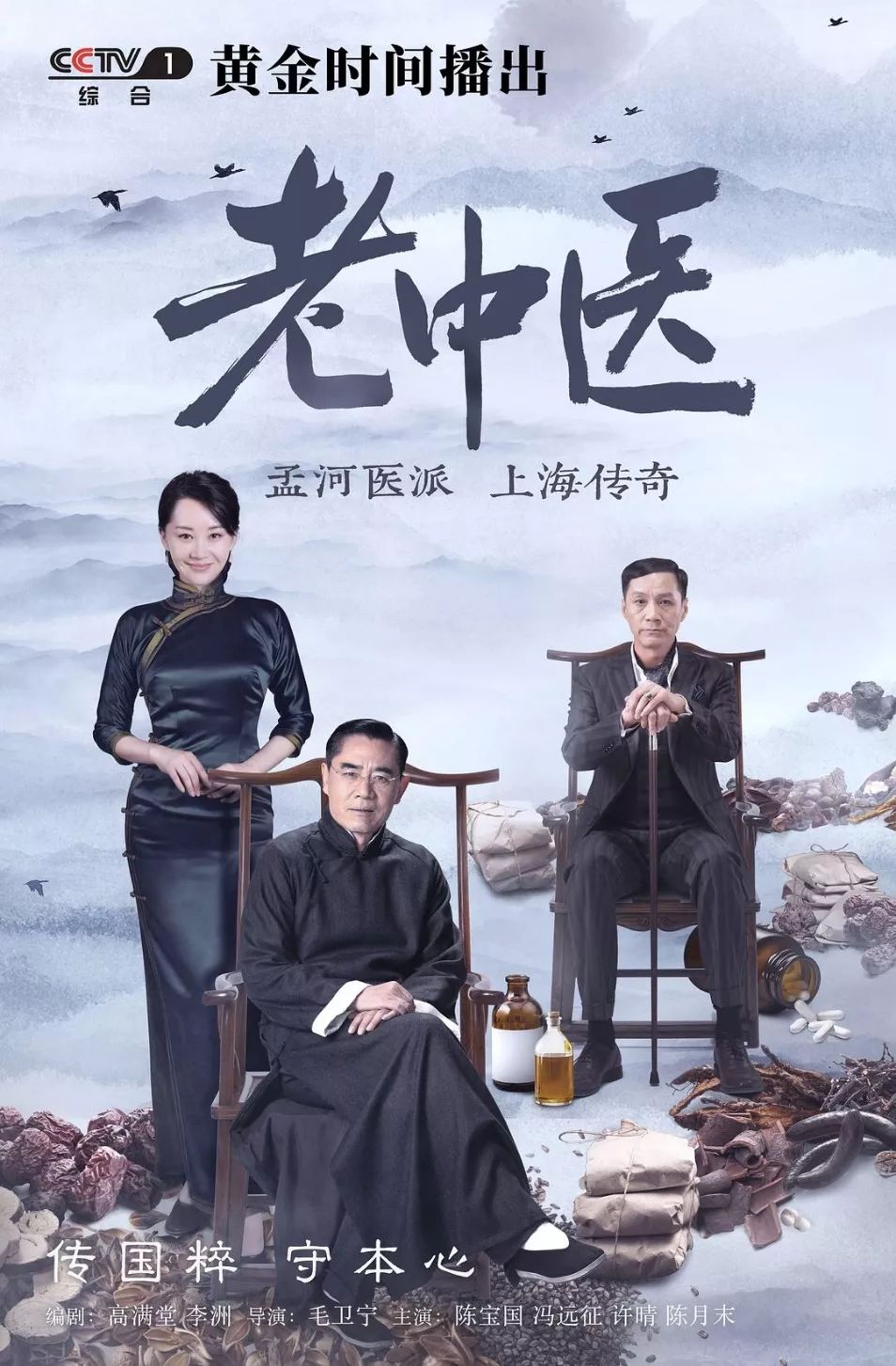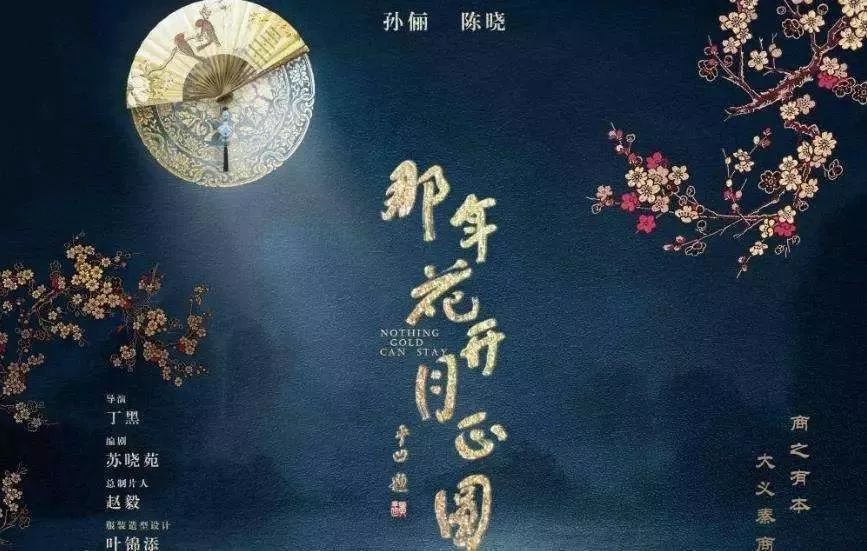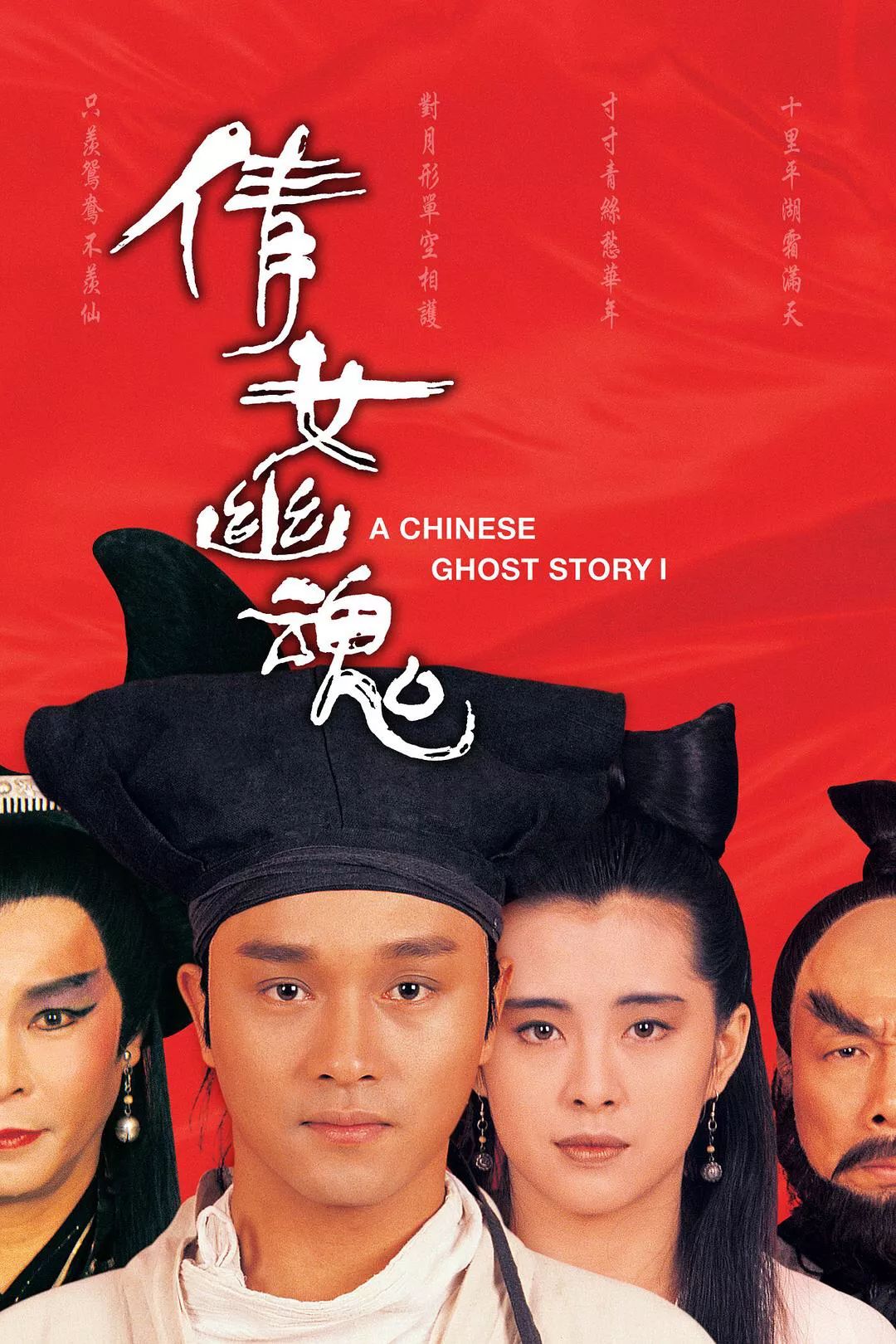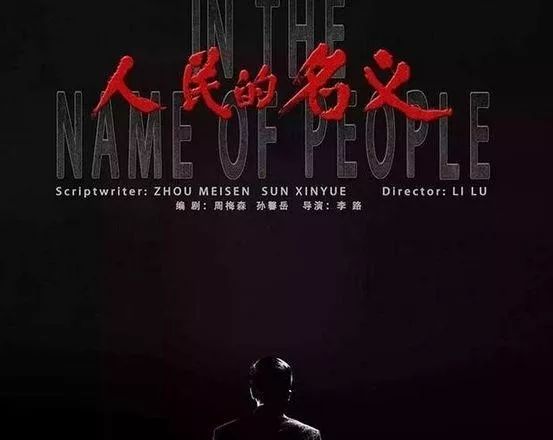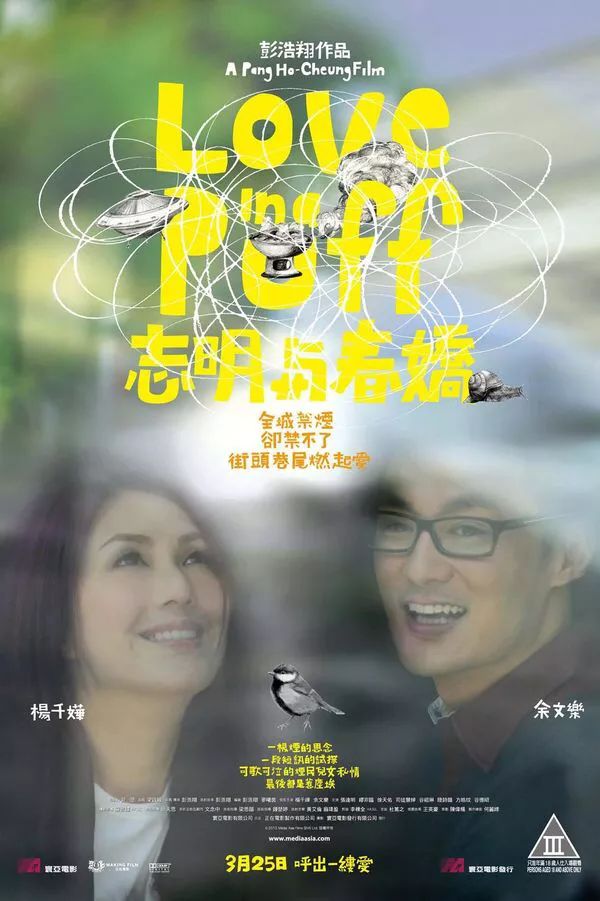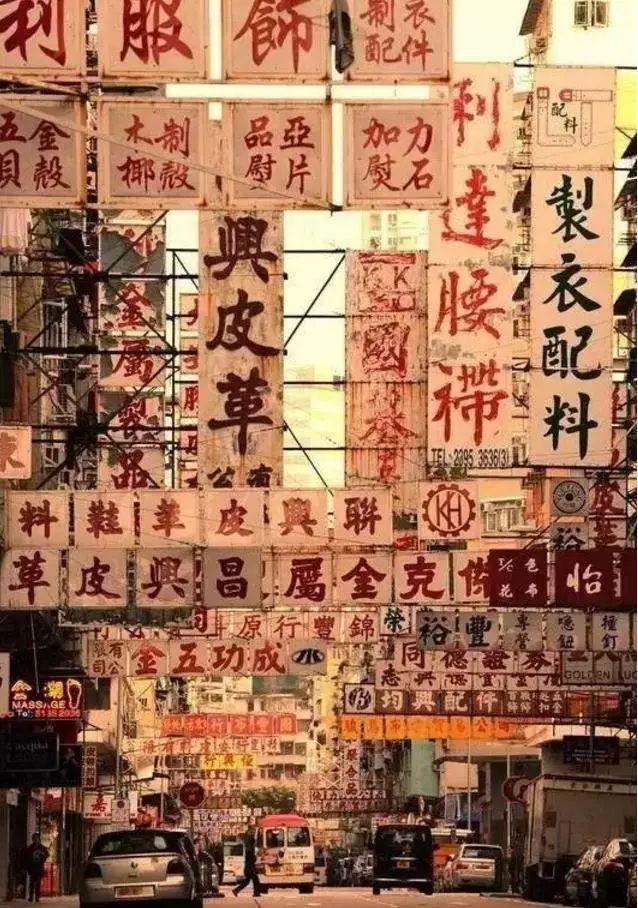
字写得好,真的可以被人记一辈子!
朋友们,最近的“国剧典范”
——《老中医》都看了吗?
网友们评价这是一部
从演员阵容到制作都非常良心的电视剧。
虽然剧情是介绍中医的,
许多人却把它当成了书法软广。
比如老中医在传授医道时提到,
学医排在第一位的是:写一手好字,
以及片头上气场十足的“老中医”三个字。
对书法史稍有了解的朋友就能看出,
这字是黄庭坚的长枪大戟的开张体势,
这种气派跟《老中医》剧情里,
誓死保卫中华瑰宝的精神如出一辙。
但这字具体是哪位书法家写的,
目前还没有人扒出来。
不过,
今天我们为大家扒了其他热播剧片头。
讲述清末陕西女首富周莹传奇一生的电视剧
——《那年花开月正圆》,
大家肯定还有印象。
片头是著名作家贾平凹题写的。
《那年花开月正圆》剧照
有人评价这七个字:
“用笔不讲究,但格调很高,
还能在字里行间看出禅意,
不失为一种独特的风格。”
贾老师的书法有没有禅意我不敢肯定,
我可以肯定的是,在众多片头里这很特别,
另一部看得人们热血澎湃的
“中国顶级政治剧”——《人民的名义》
片头背后也大有乾坤。
“人民的名义”五个字用的是颜体楷书,
楷书书体中正朴厚,一笔一画,郑重其事,
与反腐题材剧情相吻合,
试想,如果变成行书或者草书,
都会显得不够庄重,
也达不到正气凛然的效果。
颜真卿是一名出色的政治家,
安史之乱时,他的兄弟和侄子挺身而出,
却惨遭杀害,
颜真卿在极度悲愤的情况下
写了千古名篇《祭侄文稿》。
颜真卿 《祭侄文稿》
他的耿直与忠诚
形成了雄浑、宽厚、中正的颜体书风。
自此,颜体也成为正义的化身。
另一个收视爆红的抗日剧《亮剑》,
生动刻画了中国军人的
优良传统和坚忍不拔的信念。
《亮剑》剧照
这部剧的题字也是气势磅礴,凝重雄浑,
隐隐透出一股浩然正气。
导演在众多作品中,
一眼挑中了这幅苍劲挺拔的字。
“亮剑”的主人是军人出身的崔根峰将军,
他写出了军人的气质与情怀,
写出了他舒朗豁达的人生观,
也写出了导演心中的“亮剑”,
以及剧本要求的植根传统
而又冲出重围的创新精神。
崔根峰 《亮剑》
崔将军在繁忙的军事工作之余
坚持研习王羲之《兰亭序》、
颜真卿《千字文》、岳飞《出师表》等作品,
从临帖开始,渐入佳境,自成风格。
世人评价他的书法
“以军人的阳刚为主调,
给人以大江东去、一泻千里的汪洋之感,
亦不乏杨柳岸晓风残月的艺术温情与浪漫”。
和前面被人熟知的书法名家不一样,
接下来要介绍的这位片头题字者,
他的作品就有多出名,
大家就对他有多陌生。
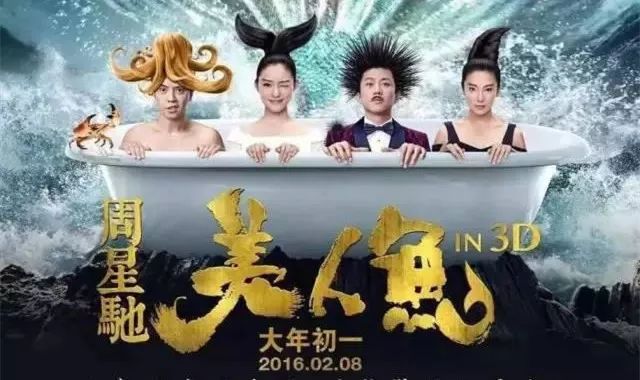
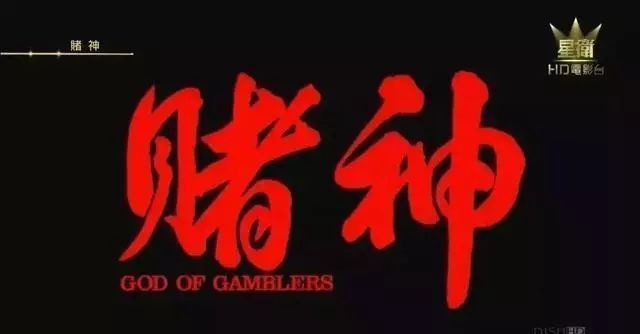
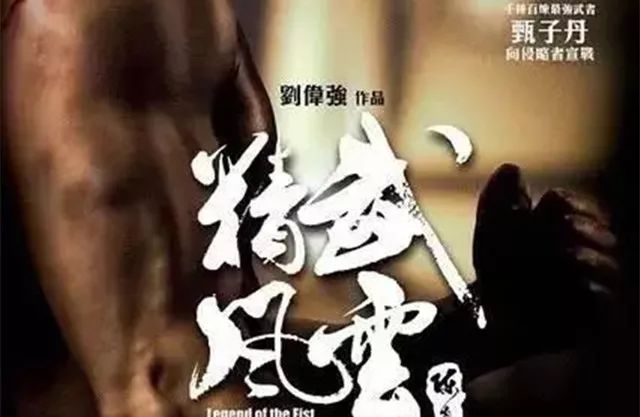
《美人鱼》、《赌神》、《叶问》……
几乎所有你能想到的港片,
片头题字都出自同一个人——冯兆华。
1989年,他在广东街头的摊位上写字,
苍劲有力的笔锋被洪金宝看中,
洪金宝邀他为自己的武打电影写片名,
慢慢地,给电影写片名成为他的副业。
他还会在书法中加入自己对剧本的理解,
比如《倩女幽魂》要写出幽幽怨怨的感觉。
《叶问》要写出咏春拳里的劲道、利落,
《叶问前传》里叶问还未成名,
他就决定写得干瘦、内敛一些。
《志明与春娇》讲述爱情的剧本,
他就写得女性化一些,柔软一些。
这些风格迥异的片名,
不细看都不知道是同一个人写的。
《志明与春娇》剧照
除了片头,港片街道上形形色色的招牌,
也有一大部分出自他之手。
港片剧照中的招牌大多出自冯兆华之手
因为招牌写得足够多,
久而久之他还总结出了写店铺招牌的心得:
酒楼的字要敦厚宽容,
书院的要端庄稳重,
武馆社团主要看气势……
他这一写就是30年,
在当今电脑造字风行的时代,
他的手写体仍然是港产片的宠儿!
接下来这组片头题字如果你们都有印象,
那么发际线的事情大家也可以释怀了。
如今我们还用书法写片头,
是为了追求良心制作和突出个性。
但在上世纪,
电视剧后期技术没那么发达的时候,
字幕片头用手写是无奈之举。
现在看来这“粗制滥造”的后期
也成为一代人挥之不去的记忆。
首当其冲是87版电视剧《红楼梦》:
《红楼梦》剧照
“红楼梦”三字由著名书法家沈尹默题写,
沈先生早年留学日本,
后任北京大学教授和校长,
民国初年,
书坛就有“南沈北于(右任)”之称。
当人民文学出版社主编
在为小说题写抬头伤神时,
想起了既是书法家又是红学爱好者的沈尹默。
他可是那个2000度近视几乎失明,
还能写蝇头小楷的书法神人啊!
《红楼梦》字幕:满纸荒唐言,一把辛酸泪!都云作者痴,谁解其中味?
沈尹默先生一生 “遍临历代碑帖”,
书法中飘逸出清雅自然的书卷气。
他最大成就在正书和行书,
临写《兰亭序》、《寒食诗》、
《蜀素帖》以及褚遂良书法等,
无论结构还是点画,形还是神,
简直无可挑剔,
以至于于右任甚至连沈先生的草稿
都要捡起来装裱珍藏。
沈尹默作品
但这也是他为人诟病的原因,
他们认为沈先生书法继承多于创造,
在风格上,又有一味甜俗之嫌。
我们到底该怎么评价?
借用陈独秀的一句诗来回答:
“书法由来见性真”,
只要是性情流露,率真而为,
就有它可读可观之处。
除了片头,
《红楼梦》里连字幕都是纯手写的。
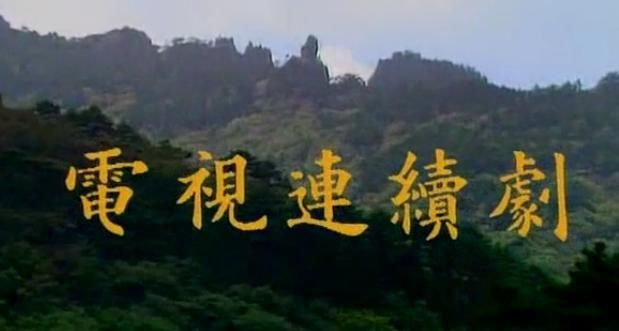
《红楼梦》手写字幕
写这些字幕的人叫李纯博,
当时他才20多岁,
他书法师从欧阳中石、刘炳森等名家,
细看他的“圆头捺”,
有几分欧阳中石的神韵在。
不光是《红楼梦》,
他也曾为上百部电视节目题写片头、字幕。
这其中有一部分是因为他是电视人。
最后作为压轴出现的,
就是电视剧《西游记》的片头。
《西游记》剧照
这是中央电视台电视剧制作中心,
在1982年开拍的《西游记》时,
邀请陈叔亮先生应题写的。
在书法创作上,
陈叔亮反对“言必称二王”、
“笔笔有出处”的教条主义,
主张广泛地向历代名家的长处学习。
明确提出书法“四新一变”主张:
新的结构、新的笔意、新的气势、
新的面目、一生求变。
陈叔亮《中国画报》
一方面,他虚心地拜古人为师,
坚持读碑、临池的日课。
另一方面,
他不断地在揣摩属于自己的、
新鲜的艺术风格和形式,
反对手法上的一成不变。
在众多字体中,陈先生尤其擅长草书,
著名书法家赵朴初这样评价他:
“多能不独张颠草,满纸云烟见性真”。
今天的片头就给大家扒到这儿了,
看了这些影视作品中书法,我更加坚信:
即使几十年后技术更进一步,
总会有一片天地是留给书法的。
很多年以后,
我可能记不清
《西游记》片头里师徒四人的排位,
记不清他们的经典动作,
但我一定会记得“西游记”三个字,
记得这渲染剧情气氛的重要一笔,
这应该就是书法的魅力吧!